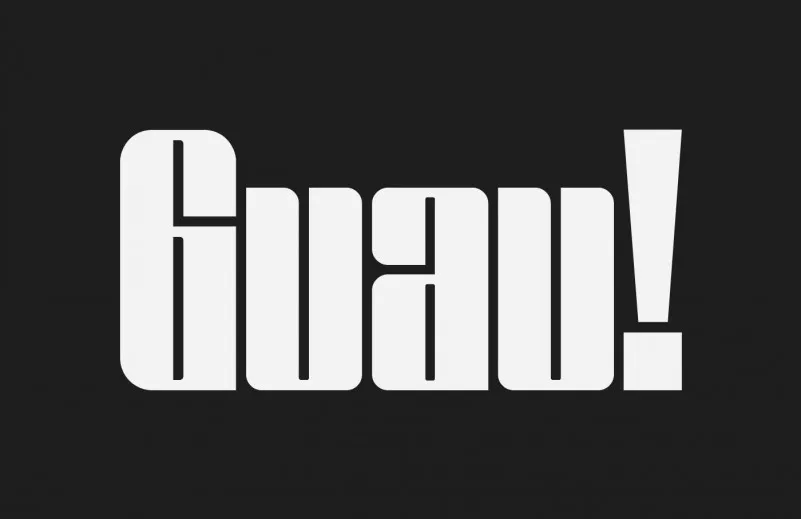
Chappa Display Font
A Chappa Display Font é uma tipografia exibição com forte apelo esportivo que se destaca na categoria das fuentes sans serif alta contraste. Ela oferece visão clara e distinta, ideal para aplicações variadas como revistas, cartazes, etiquetas, headlines ou banners. A fonte inclui dois estilos principais – Regular e Oblique – e apresenta letras maiúsculas e minúsculas, números e símbolos. Adicionalmente, ela suporta múltiplas línguas, o que expande suas possibilidades de uso para diferentes audiências internacionais. Seja para personalizar seus layouts gráficos ou para apresentar seus materiais de uma maneira mais atraente e clara, a Chappa Display Font é perfeita para diversos ambientes e necessidades.